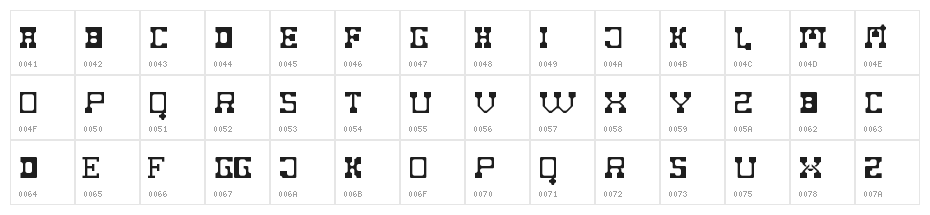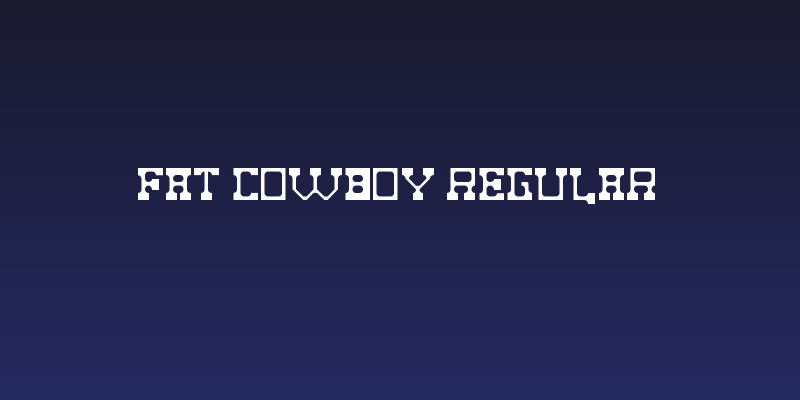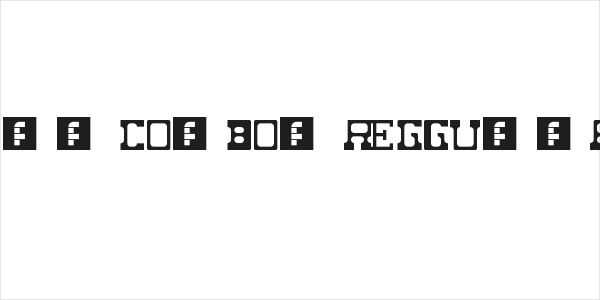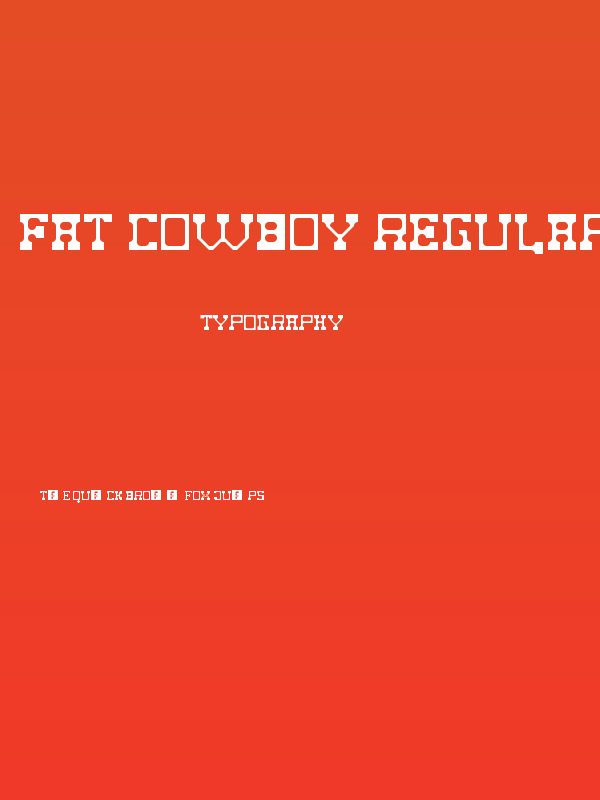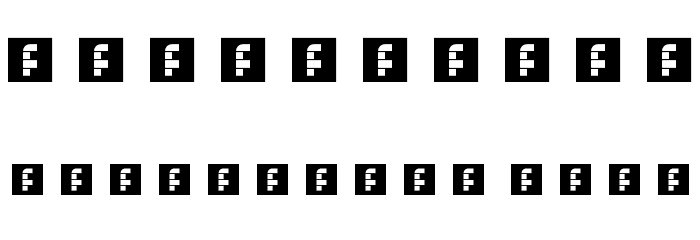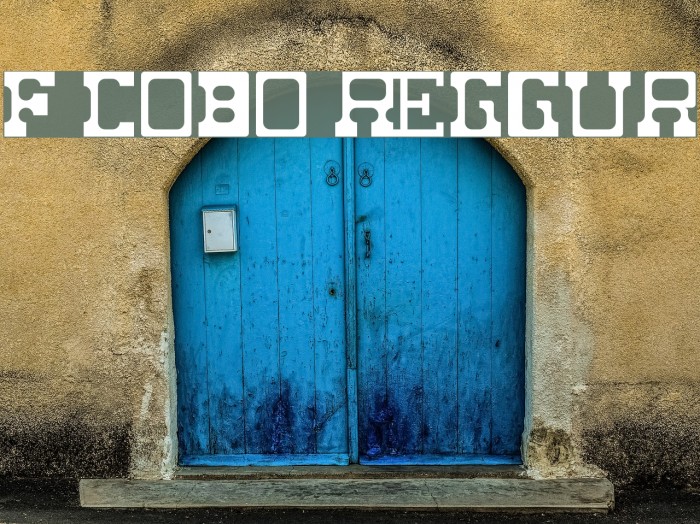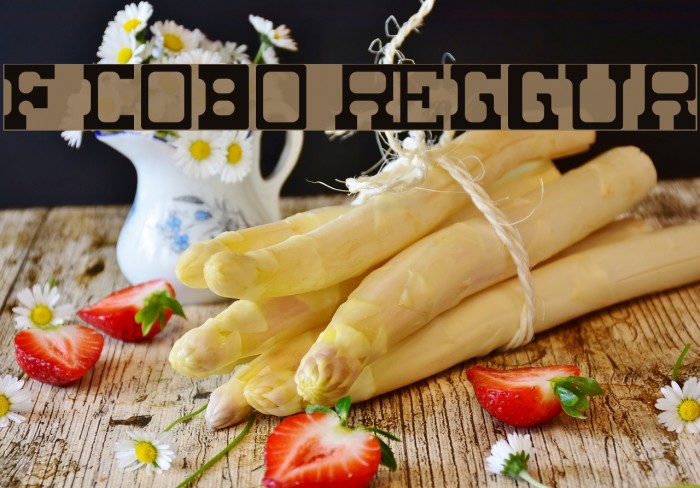
Fat Cowboy Regular Font
✎ Western
| Proiecte propuse | Ideal for Western-themed posters, event flyers, branding for cowboy or rustic-themed businesses, and any design requiring a strong, thematic presence. |